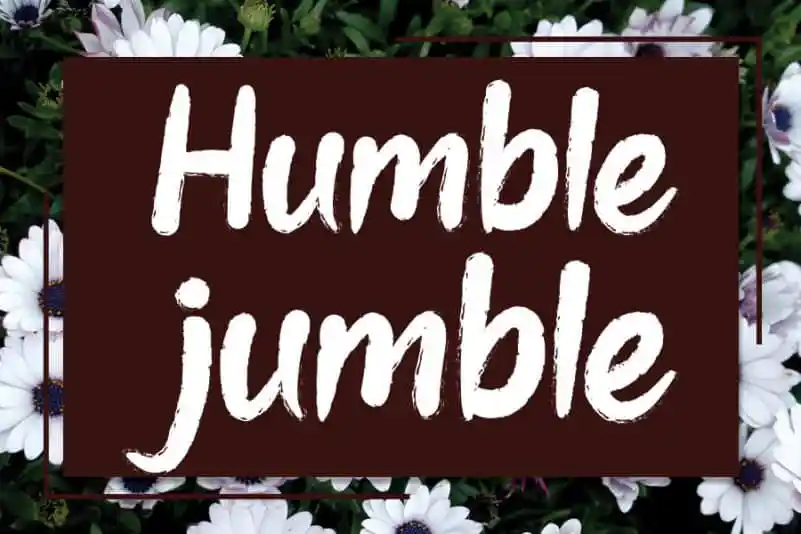
Humble jumble Brush Font – Download Grátis
A fonte ‘Humble jumble Brush Font’ é uma perfeita escolha para quem busca algo único e envolvente no seu design gráfico. Esta elegante fonte script, criada com a ajuda de um pen brush, oferece estilo distintivo e sofisticado que não pode deixar ninguém indiferente. Seu design fluído e autêntico é perfeito para dar uma personalidade única aos seus trabalhos. Ideal tanto para aplicação em projetos gráficos profissionais quanto para criações artísticas de alto nível, esta fonte é uma verdadeira atração para designers apaixonados por estilos alternativos. Com ‘Humble jumble Brush Font’, você pode transformar ideias simples e únicas em obras de arte única no seu campo.